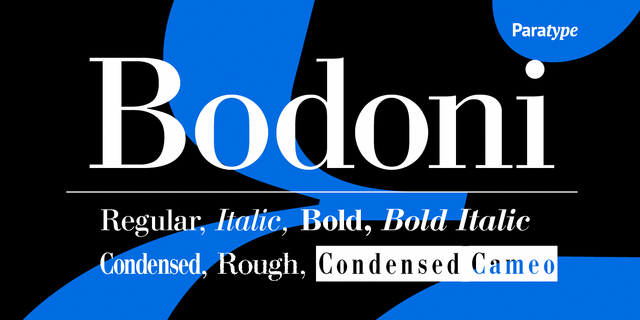
Гарнитура разработана в фирме ПараТайп (ПараГраф) в 1989 (дизайнер Александр Тарбеев) по мотивам современных вариантов шрифтов итальянского гравера и типографа конца XVIII века Джамбатиста Бодони. Бодони был директором типографии герцога Пармского. Его ранние работы повторяли рисунок гарнитур Фурнье и Дидо, но по мере развития мастерства Бодони его шрифты стали считаться первыми среди шрифтов нового стиля. Его буквы имеют абсолютно вертикальные овалы без наклона осей, сильно контрастирующие основные и соединительные штрихи и длинные острые нескругленные засечки. Контраст толстых и тонких штрихов в шрифтах Бодони может производить эффект мерцания полосы набора, поэтому их надо аккуратно применять в тексте, но они хороши для заголовков и акцидентных работ. Узкое начертание было добавлено в 1993.
ровный, богатый, классический, интеллигентный, аристократичный, салонный, торжественный, звонкий, статичный, благородный, точный, мастерский, дорогой, традиционный, качественный, культурный, эстетичный, знаменитый, драгоценный, отборный, острый, стройный, тесный, антикварный, ностальгический, старомодный, старинный, исторический, гордый, театральный, драматичный, гламурный